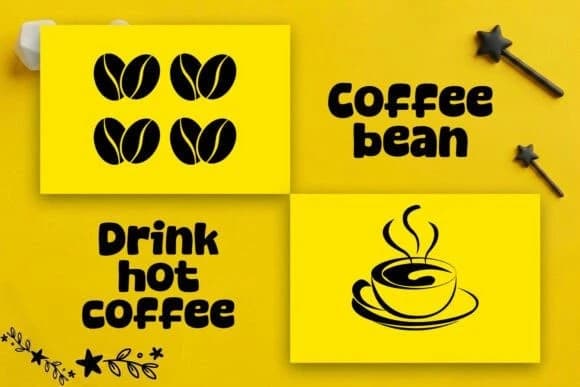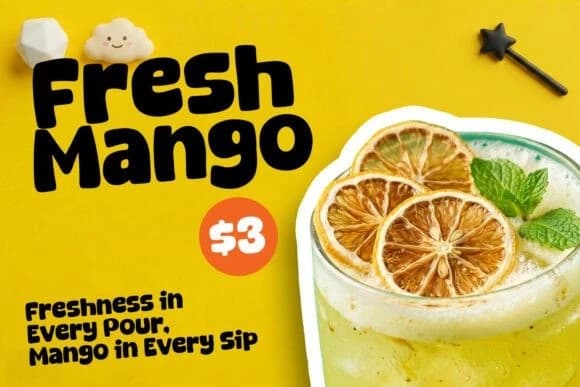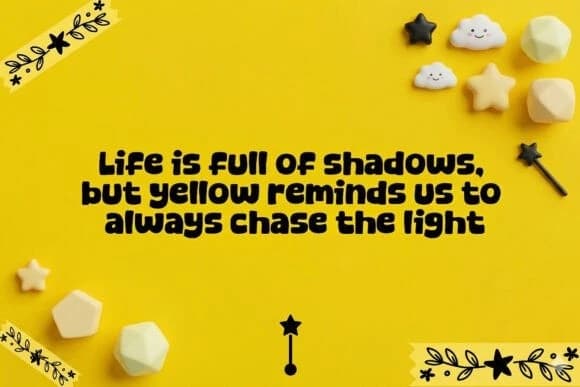
Magic Yellow Font
Magic Yellow Font, posterler, logolar, dergiler, kapaklar, afişler ve çok daha fazlası için mükemmel olan modern ve sevimli bir gösterim yazı tipidir. Bu harika fontu edinin ve bunu kullanarak hoş tasarımlar yaratın. İnanılmaz geniş bir proje yelpazesine kolayca uyum sağlar.
Magic Yellow Font, posterler, logolar, dergiler, kapaklar, afişler ve çok daha fazlası için mükemmel, modern ve sevimli bir gösterim yazı tipidir! Bu harika yazı tipini edinin ve hoş tasarımlar yaratmak için kullanın. Oldukça geniş bir proje yelpazesine kolayca uyum sağlar.
Magic Yellow